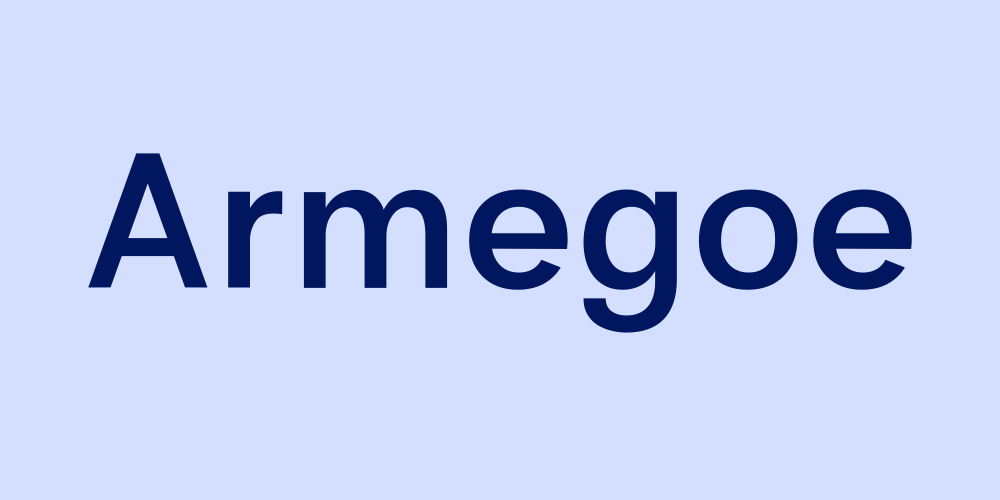
A Armegoe é uma nova adição à família das fuentes sans serif que oferece simplicidade e modernidade em cada caractere. Desenvolvida pelo designer Hamilton, esta fonte é perfeita para gráficos digitais contemporâneos que valorizam a velocidade de leitura. Suas linhas clean e agradáveis ao olho permitem uma experiência fluida nos materiais impressos ou exibidos online. Com sua linguagem suave, a Armegoe oferece uma combinação perfeita entre clareza e estilo moderno, tornando-a ideal para aplicativos como design gráfico, logotipos digitais, e conteúdo informativo. Seja em um layout de newsletter ou em um site web rápido e funcional, a Armegoe traz elegância com simplicidade, tornando sua utilização uma escolha óbvia na sua próxima criação visual.